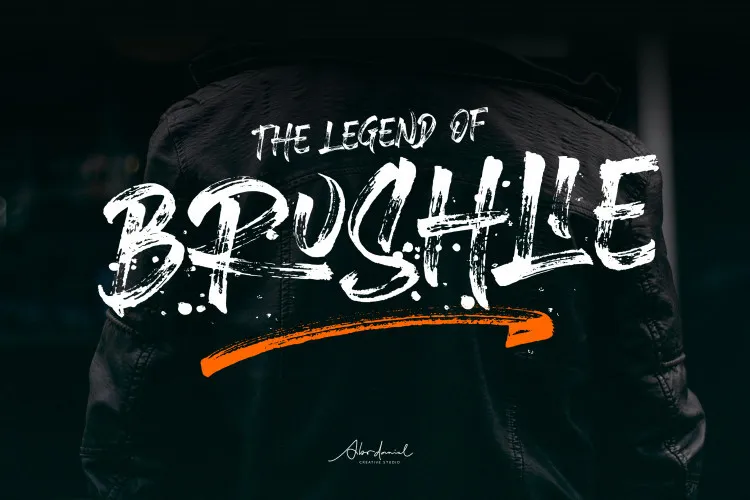
Brushlie Brush Font – Download Grátis
A nova fonte Brushlie foi criada pelo Abo Daniel Studio com uma técnica de tração que remete aos pincéis reais, oferecendo um toque fresco e natural à sua escolha. Esta é uma fonte brush-texturizada, adaptada a uma abordagem contemporânea da design, elaborada artesanalmente com linhas naturais e um desvio na base de traço. Está ideal para criar logotipos, roupas personalizadas ou embalagens de produtos que precisam de uma tipografia natural e única, proporcionando ao seu design um toque autêntico que se assemelha aos pincéis reais. Apenas com Brushlie, você pode expressar sua identidade gráfica de forma elegante, moderna e pessoalmente convidativa.